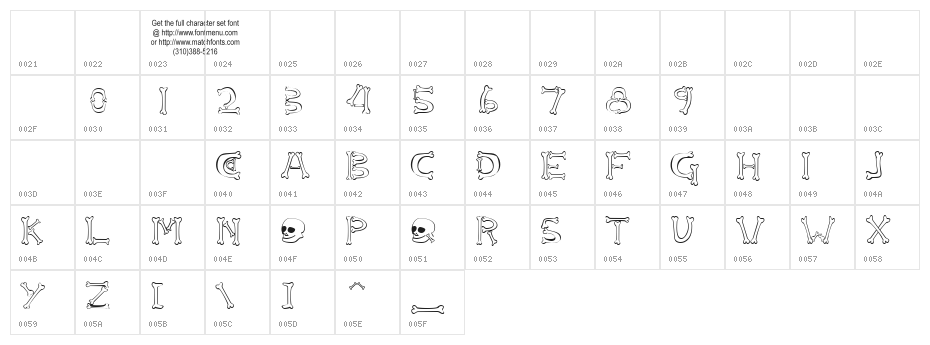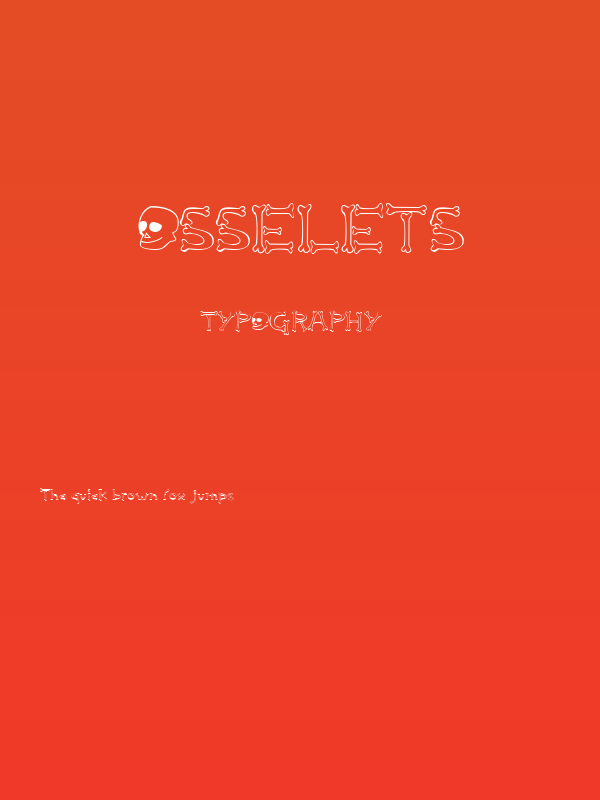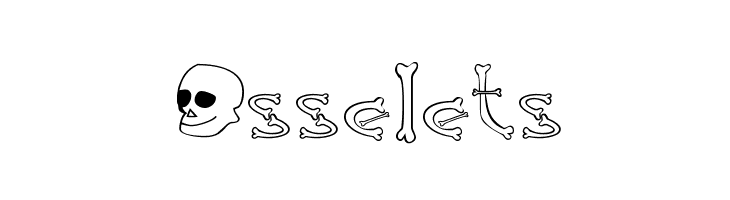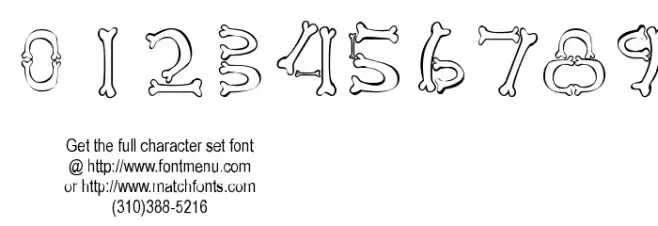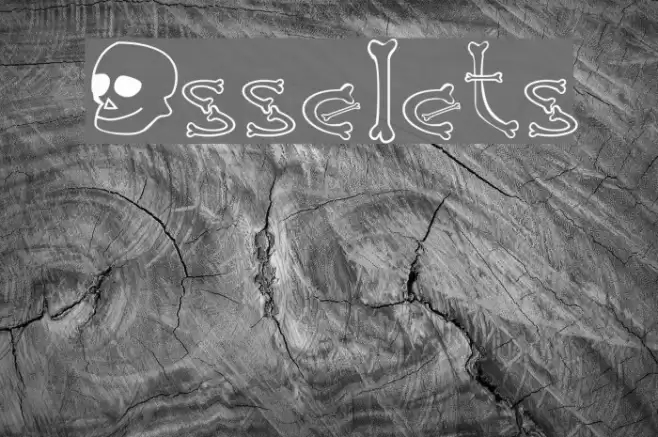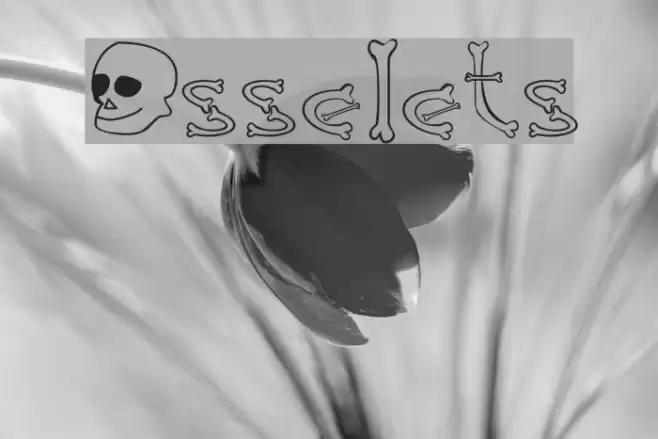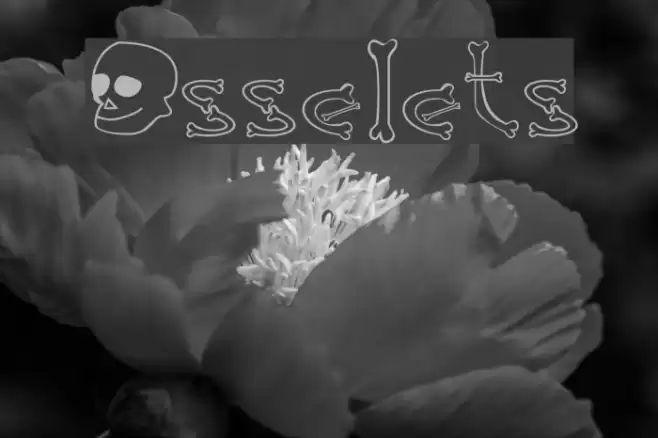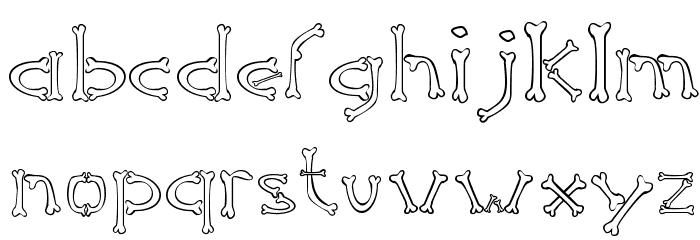
Osselets Font
| Categorie | Outline |
| Progetti proposti | Ideal for Halloween invitations, horror-themed posters, party decorations, and creative projects needing a spooky touch. |